CSS Web 安全字体
什么是 Web 安全字体?
Web 安全字体是在所有浏览器和设备上通用安装的字体。
回退字体
但是,没有 100% 完全安全的字体。总有一个 找不到字体或未正确安装字体的可能性。
因此,始终使用后备字体非常重要。
这意味着您应该在 该物业。如果 第一个字体不起作用,浏览器将尝试下一个,下一个,依此类推。 始终以通用字体系列名称结束列表。font-family
1 | 在这里,有三种字体类型:Tahoma、Verdana 和 无衬线。第二种和第三种字体是备份,以防找不到第一种字体。 |
适用于 HTML 和 CSS 的最佳 Web 安全字体
以下列表是 HTML 和 CSS 的最佳 Web 安全字体:
- Arial (sans-serif)
- Verdana (sans-serif)
- Tahoma (无衬线)
- 投石机MS(无衬线)
- Times New Roman(衬线)
- 格鲁吉亚(衬线)
- Garamond(衬线)
- Courier New(等宽)
- Brush Script MT(草书)
注意: 在发布网站之前,请务必检查您的 字体出现在不同的浏览器和设备上,并且始终使用后备字体!
Arial (sans-serif)
Arial 是在线和印刷媒体中使用最广泛的字体。阿里亚尔 也是 Google 文档中的默认字体。
Arial 是最安全的网络字体之一,它适用于所有主要操作系统。
例
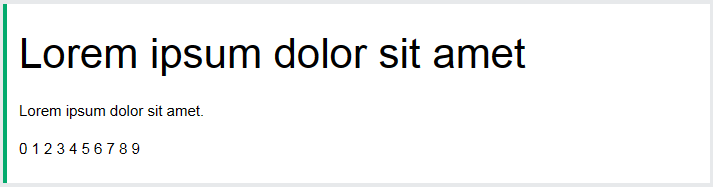
Verdana (sans-serif)
Verdana是一种非常流行的字体。Verdana 即使字体很小,也很容易阅读。
例
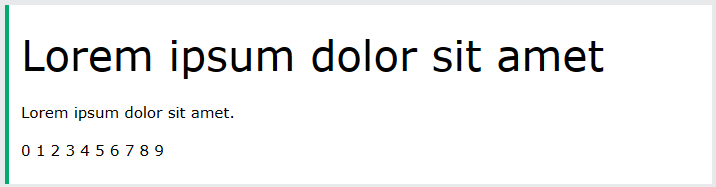
Tahoma (无衬线)
Tahoma 字体的字符间距较小。
例
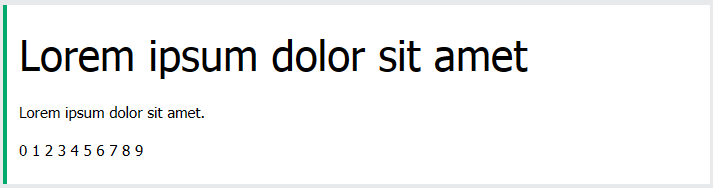
Trebuchet MS(无衬线)
Trebuchet MS由Microsoft于1996年设计。请谨慎使用此字体。不 所有移动操作系统均支持。
例
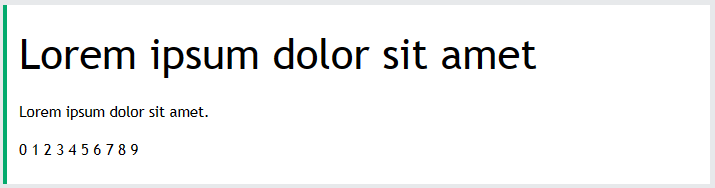
Times New Roman(衬线)
Times New Roman 是世界上最知名的字体之一。它看起来 专业,用于许多报纸和“新闻”网站。它也是 Windows 设备和应用程序的主要字体。
例
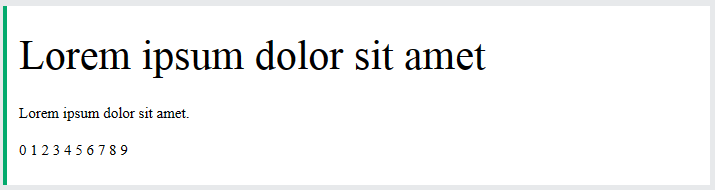
Georgia
Georgia 是一种优雅的衬线字体。它在不同的字体大小下都非常可读,因此它是移动响应式设计的一个很好的候选者。
例
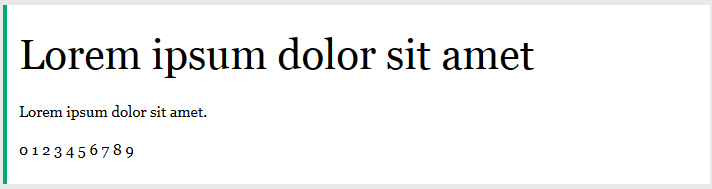
Garamond(衬线)
Garamond 是一种用于许多印刷书籍的经典字体。它有一个永恒的 外观和良好的可读性。
例
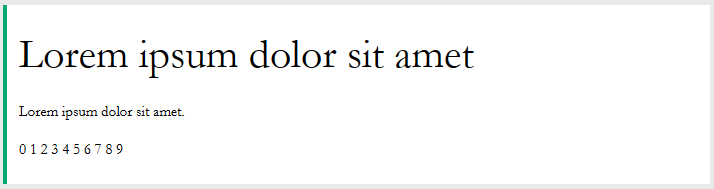
Courier New(等宽)
Courier New 是使用最广泛的等宽衬线字体。 Courier New 通常与编码显示和许多电子邮件提供商一起使用 将其用作默认字体。Courier New 也是电影的标准字体剧本。
例
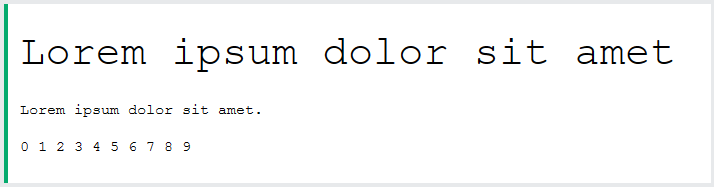
Brush Script MT(草书)
Brush Script MT 字体旨在模仿手写内容。 它优雅而精致,但可能难以阅读。请谨慎使用。
例